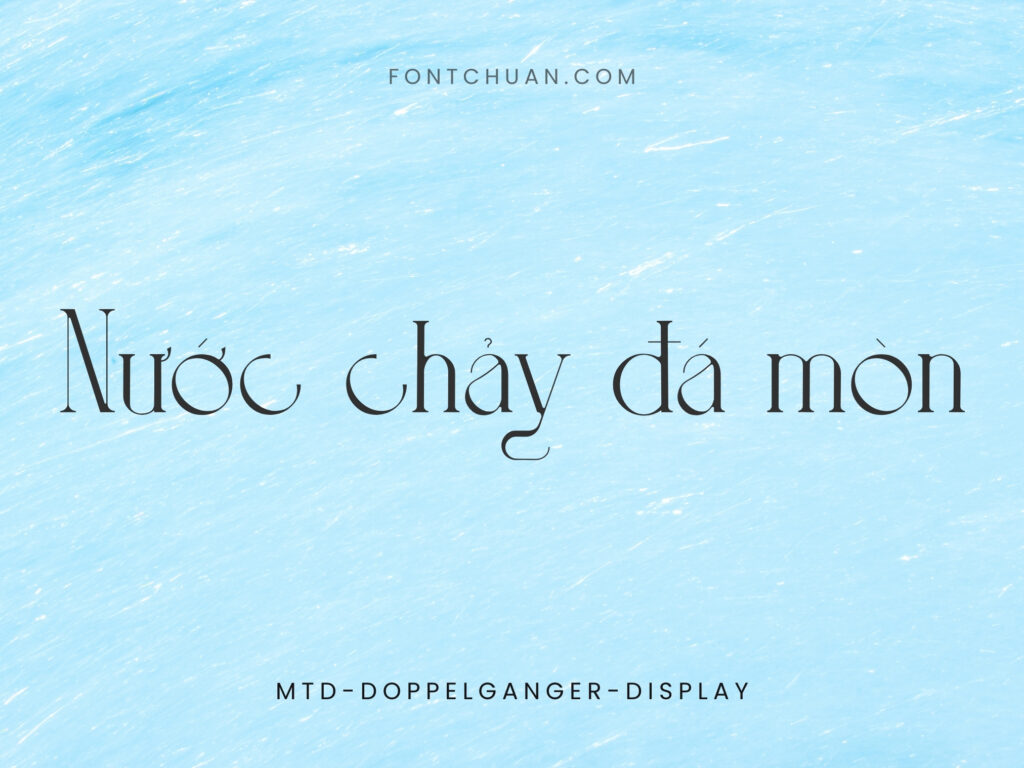
Font MTD Doppelganger Display là một kiểu chữ serif hiển thị lấy cảm hứng từ phong cách retro, được thiết kế bởi Casper Schutte và đã được Việt hóa bởi Mộc Hạ. Font này hỗ trợ đầy đủ tiếng Việt cùng hơn 90 ngôn ngữ khác, mở rộng khả năng ứng dụng trong các thiết kế đa ngôn ngữ. Đây là một trong những phông chữ được cộng đồng thiết kế đánh giá cao và sử dụng trong nhiều dự án sáng tạo, đáp ứng nhu cầu đa dạng của người dùng.
MTD Doppelganger Display nổi bật với các đường nét độc đáo và hình dạng kỳ lạ, tạo cảm giác hoài cổ nhưng vẫn hiện đại. Font rất phù hợp cho các thiết kế logo, tiêu đề, bao bì sản phẩm, thiệp mời và các ấn phẩm đòi hỏi sự sáng tạo và nổi bật. Các ngành nghề phù hợp bao gồm quảng cáo, giáo dục và công nghệ. Font này cũng lý tưởng cho các sự kiện như Tết, Giáng sinh, Valentine và các lễ hội khác.